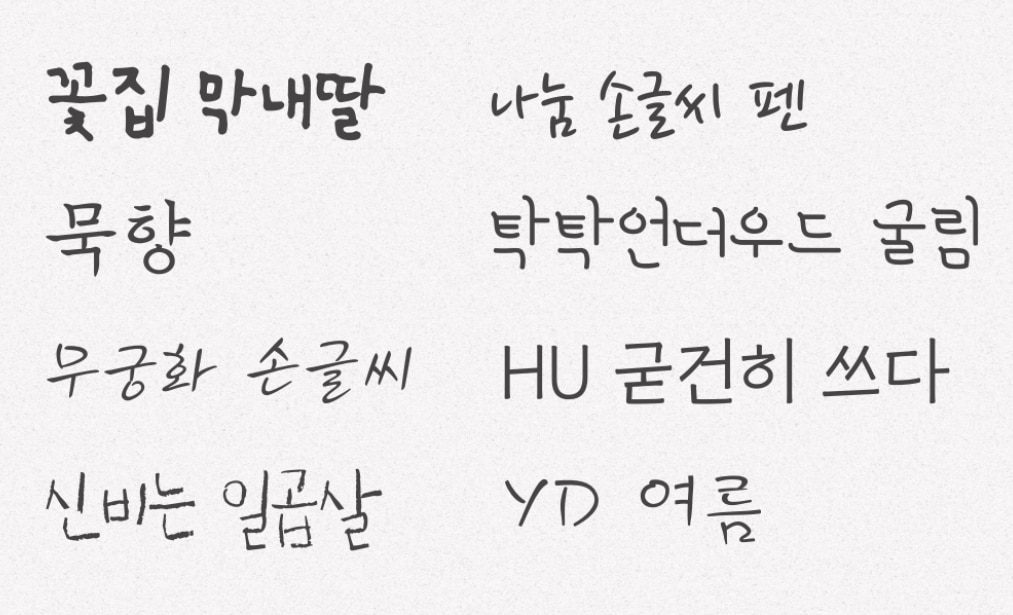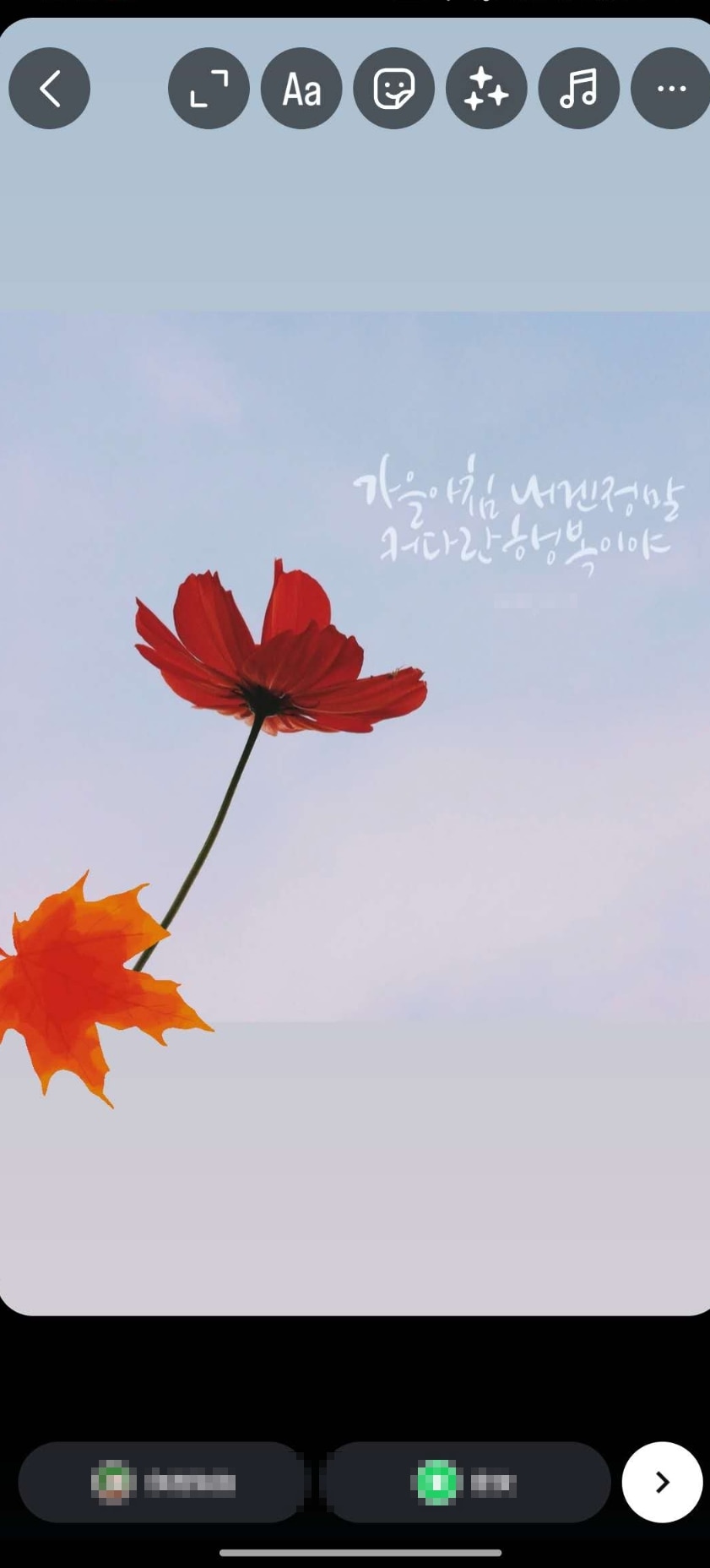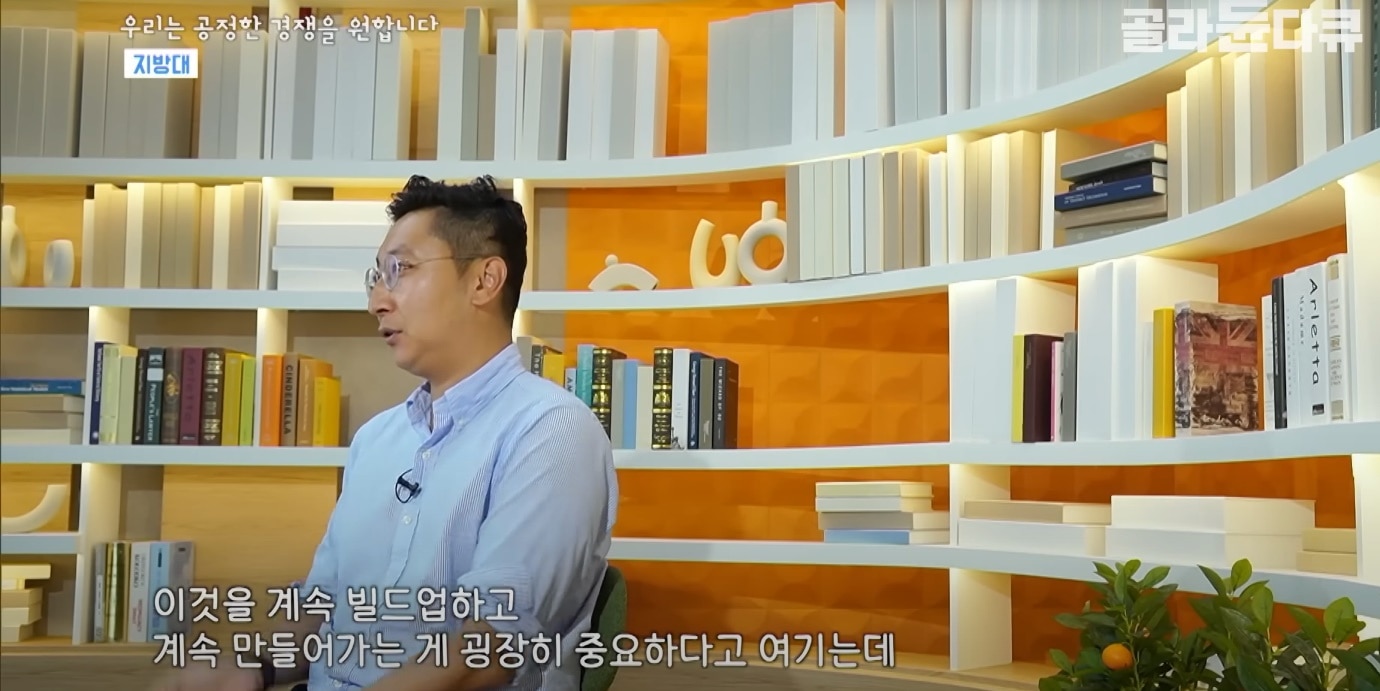
인스타 스토리 자막 폰트, 이렇게만 고르면 조회수 달라집니다!
짧은 인스타 스토리 속에서도 글자가 감각적으로 들어가면 더 세련돼 보이고, 릴스에서 강렬한 폰트는 스크롤을 멈추게 만듭니다. 반대로 가독성 떨어지는 폰트를 쓰면 아무리 좋은 영상도 금세 흘려보내게 되죠. 그래서 요즘 인플루언서와 브랜드 계정은 자막 폰트 선택에 굉장히 신경을 씁니다.
이번 글에서는 인스타 자막 폰트 추천 리스트 및 스토리에 잘 어울리는 감성 폰트, 그리고 Filmora로 손쉽게 적용하는 방법까지 모두 담았습니다. 단순히 예쁜 인스타 스토리 자막 폰트 고르기가 아니라, 영상 완성도를 높이고 조회수를 끌어올리는 전략적인 자막 활용법을 알려드릴게요.
파트 1. 왜 인스타 자막 폰트가 중요한가?
인스타그램에서 영상은 단순히 보여주는 것에 그치지 않습니다. 짧은 스토리 한 컷, 15초 릴스, 그리고 피드 영상 하나까지 모두 시선을 붙잡고 메시지를 전달하는 도구죠. 예를 들어 같은 문장이라도, 손글씨 스타일 폰트를 쓰면 감성적인 분위기를, 굵은 산세리프 폰트를 쓰면 강렬하고 세련된 인상을 줄 수 있습니다. 즉, 자막 폰트는 단순한 글꼴이 아니라 영상의 분위기와 몰입도를 조절하는 장치라고 할 수 있어요.
손글씨 자막 폰트
인스타 스토리 자막 폰트를 고를 때는 다음 3가지 요소를 꼭 고려해야 합니다.
• 가독성: 모바일 시청이 대부분인 만큼 작은 화면에서도 선명하게 읽혀야 합니다.
• 분위기: 영상이 브이로그인지, 광고인지, 정보 전달용인지에 따라 어울리는 폰트가 달라집니다.
인스타 스토리 폰트
또한 인스타와 유튜브의 자막 폰트 차이도 알아야 하는데요. 유튜브는 강의나 브이로그처럼 롱폼 영상이 많아 안정적이고 눈에 부담 없는 자막 폰트가 선호됩니다. 반면 인스타는 스토리와 릴스 같은 숏폼 영상이 중심이므로, 순간적으로 눈길을 끌고 감각적인 분위기를 살려주는 자막 폰트가 효과적입니다.
유튜브 자막
파트 2. 인스타 스토리 자막 폰트 추천 Top 10
구분 폰트명 특징 활용 추천 폰트 예시
썸네일/타이틀 Black Han Sans 굵고 힘 있는 스타일, 임팩트 강조 썸네일, 타이틀
Black Han Sans
썸네일/타이틀 Montserrat Bold 세련되고 깔끔한 영문 폰트 글로벌 감성, 타이틀
Montserrat Bold
스토리 배민 주아체 손글씨 느낌, 따뜻한 분위기 감성 스토리, 브이로그
배민 주아체
스토리 Café24 동동체 귀엽고 발랄한 느낌 일상 스토리, 릴스
Café24 동동체
브이로그 감성 에스코어 드림 부드럽고 안정적, 가독성 우수 여행, 브이로그 영상
에스코어 드림
브이로그 감성 Pretendard Regular 심플하고 현대적, 다목적 브이로그, 정보성 영상
Pretendard Regular
정보 전달 Noto Sans KR 구글 무료 고딕체, 또렷한 가독성 정보 자막, 교육 콘텐츠
Noto Sans KR
정보 전달 Open Sans 대표 영문 폰트, 심플 & 직관적 정보성 릴스, 튜토리얼
Open Sans
브랜드/광고 윤고딕 700 명확하고 전문적인 인상 브랜드 홍보, 기업 영상
윤고딕 700
브랜드/광고 Lato Bold 세련되고 간결한 영문 폰트 광고, 브랜딩 영상
Lato Bold
파트 3. 인스타 자막 폰트 추천 & 변환 툴 비교
인스타그램 기본 제공 폰트만으로는 부족한 경우, 폰트 변환 앱과 사이트를 활용하면 특별한 느낌을 줄 수 있어요. 아래 5가지는 무료 사용이 가능하면서도 인스타 스토리와 릴스에 많이 쓰이는 인기 툴입니다.
이름 특징 장점 단점
눈누(noonnu) 국내에서 가장 많이 쓰이는 무료 한글 폰트 저장소 상업적 사용 가능한 무료 한글 폰트 다수 제공, 감성적인 글꼴 다양 영문 폰트 선택지가 제한적, 웹사이트 UI가 다소 단순
Google Fonts 글로벌 무료 폰트 라이브러리 한글·영문 모두 지원, 모바일·웹 적용 쉬움, 라이선스 명확 일부 한글 폰트는 디자인 다양성이 부족
Café24 무료 폰트 Café24에서 제공하는 감성 글꼴 패키지 브랜딩에 어울리는 세련된 한글 폰트 제공, 상업적 사용 허용 영문 폰트 부족, 일부 글꼴은 가독성이 낮을 수 있음
Font Meme 입력한 문장을 다양한 스타일로 변환 설치 없이 사용 가능, 유니크한 스타일 제공 변환된 텍스트는 이미지 형태여서 편집 제약 있음
Instagram Fonts 인스타그램 전용 온라인 폰트 변환기 텍스트를 다양한 스타일(이탤릭, 굵게, 심볼 포함)로 손쉽게 변환 지나치게 화려한 폰트는 가독성 저하 우려
✅ [PC] Filmora 데스크톱 프로그램에서 인스타 자막 폰트 적용하기
PC 버전은 한 단계 더 나아갑니다. 설치된 모든 폰트를 불러와 사용할 수 있고, 자간이나 행간 조정, 그리고 애니메이션 효과까지 적용할 수 있어 브랜딩 영상이나 광고 영상에도 손색이 없습니다.
Filmora를 실행하고 새 프로젝트의 캔버스를 9:16으로 설정합니다.
필모라 데스크톱 실행
미디어를 불러와 컷 편집을 한 뒤 자막 상단의 ‘타이틀’> ‘타이틀 템플릿’> ‘일반 자막’을 누릅니다. 인스타 자막 폰트를 따로 설정하고 않아도 다양한 효과의 자막을 찾을 수 있습니다.
필모라 자막 적용
필모라 PC 버전 역시 자막 템플릿에서 영상 분위기에 맞는 샘플을 찾아 사용할 수 있습니다. 원하는 자막을 타임라인으로 드래그하고, 텍스트를 입력하면 바로 효과가 적용됩니다.
자막 폰트 추천
마지막으로 ‘내보내기’를 눌러 SNS에 업로드하세요.
이제까지 살펴본 과정을 정리해보면, Filmora는 인스타 스토리 자막 편집에 최적화된 올인원 툴이라고 할 수 있습니다. 지금 바로 Filmora를 다운로드하고, 나만의 자막 스타일로 인스타 스토리를 더 감각적이고 전문적으로 꾸며보세요.
파트 5. 인스타 스토리 자막 폰트 응용 팁
1. 혼합 폰트 스타일 – 중요한 단어만 딱!
자막 전체를 한 가지 스타일로만 쓰면 밋밋해 보일 수 있으니 핵심 단어만 굵기 처리하거나 색상을 달리 적용해 보세요. 예를 들어, “오늘만 50% 할인”이라는 문장에서 ‘50% 할인’ 부분만 굵고 빨간색으로 바꾼다면 메시지가 확실히 눈에 들어옵니다.
• Q2. 자막에 사용할 색상은 어떻게 정하는 게 좋을까요?
A. 영상 분위기에 맞춰 선택하되, 브랜드 계정이라면 브랜드 컬러를 적극 활용하는 것이 좋습니다. 단, 배경과의 대비는 반드시 확보해야 합니다.